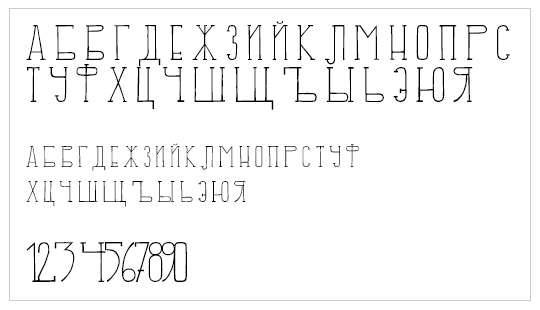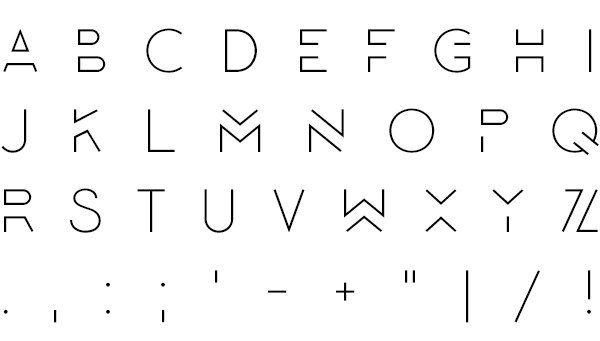
Шрифт для фотошопа русский тонкий: Тонкие шрифты — русские скачать бесплатно
Рассказываем о мощном инструменте, который идеально подойдёт для рукописных шрифтов
Некоторые шрифты можно сделать более броскими с помощью глифов и элементов, которые в английском языке называются swashes. Буквально это переводится как «плескаться» — но, разумеется, к водным процедурам это не имеет отношения.
Начертание swash — варианты букв с украшениями. Это могут быть завитки, необычные хвостики и другие элементы, которые делают символы интереснее. Глифы и swashes — необязательная добавка, они есть не для всех шрифтов.
Но если есть, то они будут соответствовать общему стилю и, соответственно, впишутся органично.
Например, в рукописных шрифтах часто есть символы для украшения первых и последних букв в слове. Для каллиграфических предусмотрены орнаменты и дополнительные завитки. Если шрифт имитирует рукописный текст, для него, как правило, характерно несколько вариантов одного и того же символа. Это позволяет сделать имитацию реалистичной, так как от руки мало кто способен выводить одинаковые буквы. В шрифтах, использующихся для заголовков, встречаются различные мотивы и иконки. Для них нередко предусмотрены и границы в разных стилях.
Что нужно для использования глифов в Photoshop
Как найти глифы в Photoshop
Для начала создайте новый файл. Затем перейдите к Photoshop Glyphs: Window > Glyphs. По умолчанию будет отображаться последний использованный шрифт.
На панели будут показаны отдельные символы. Несколько советов по работе:
- Если хотите изменить шрифт, примерите опцию «Выбрать семейство шрифтов» (Set Font Family).
- В разделе категорий шрифта (Set Font Category) вы найдёте глифы, относящиеся к конкретному шрифту.
- Чтобы выбрать стиль — курсив, тонкий, обычный, полужирный, — используйте соответствующий раздел (Set Font Style).
- Ползунок масштаба (Glyphs zoom slider) и преобразователь (Glyphs scaler) помогут увеличить и уменьшить глифы, чтобы рассмотреть их в разных размерах.
Как добавить украшения шрифта в Photoshop
Используйте инструмент Text. Кликните по полю документа, чтобы добавить надпись.
Выберите букву, и панель глифов автоматически найдёт её. Прокрутите страницу, чтобы посмотреть все доступные варианты символов. Чтобы заменить букву, дважды кликните по глифу.
На панели глифов можно выбрать Alternates for Selection в разделе категорий шрифта (Set Font Category). В этом случае вы увидите варианты украшений для выбранной вами буквы. Чтобы применить вариант, дважды кликните по нему.
Например, вот варианты для буквы m. В первом случае это обычный символ, во втором — со шлейфом, в третьем — с дополнительным элементом в начале. Украшенные варианты хороши для слов, которые начинаются или заканчиваются буквой m.
Вот как это работает: в словосочетании Modern Mountain использованы разные варианты заглавной M и строчной n.
Глифы и завитки есть не у каждого шрифта. Но если вы работаете с Photoshop, в вашей библиотеке наверняка найдутся те, с которыми можно опробовать эту опцию. Благодаря ей рукописные шрифты в ваших работах станут выглядеть красивее и естественнее.
Но имейте в виду: с украшениями легко перестараться. Несколько лишних символов могут превратить изысканное начертание в нелепый китч. Потому надо знать меру и помнить об уместности.
Красивые бесплатные декоративные шрифты для фотошопа
Свежая подборка красивых бесплатных декоративных шрифтов для фотошопа. Почему именно для фотошопа? Все просто — эти шрифты чисто декоративные. Из них не имеет смысла набирать длинные тесты.
Декоративные шрифты можно с успехом использовать в отрисовке всевозможных флаеров, свадебных приглашений, для плакатов, афиш, вывесок, тату, баннеров и в веб-дизайне, разумеется, тоже.